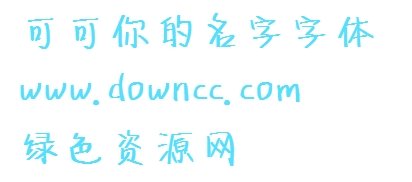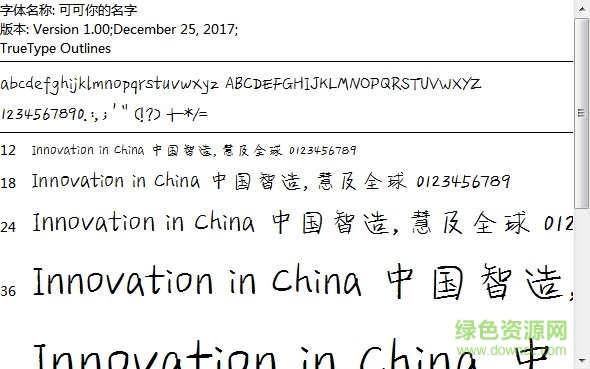
可可你的名字字體字跡清寂而穩(wěn)重,筆畫中肯而樸實,給中國文字不一樣的表達方式,盡顯本真之態(tài),給你的設(shè)計不一樣的出彩體驗,綠色資源網(wǎng)歡迎大家免費下載!
你的名字字體是可可系列字體中最大方簡潔的一款,由設(shè)計師子盟創(chuàng)作,文筆溫柔而含蓄,英文流暢中文簡潔,可愛十足哦!